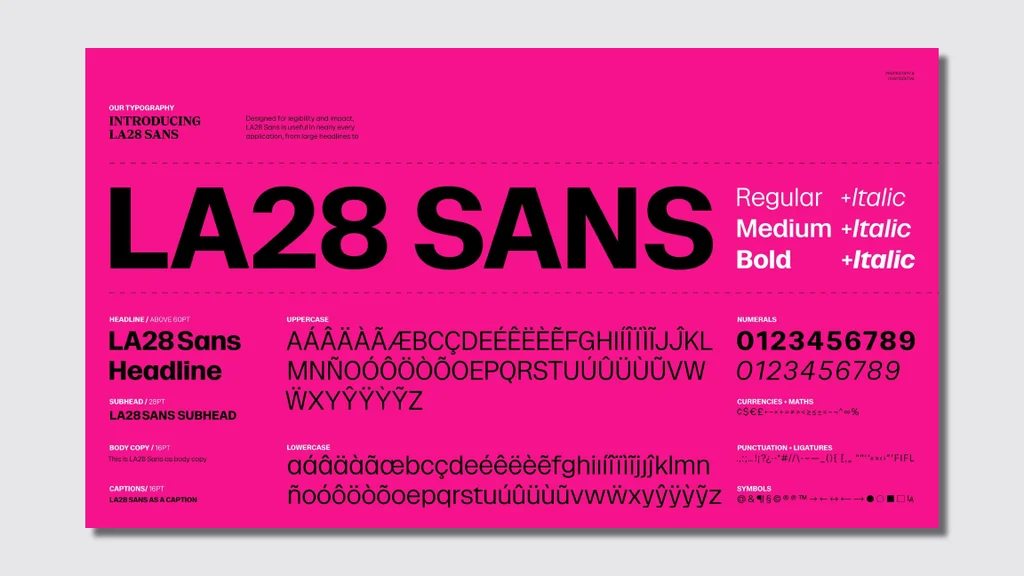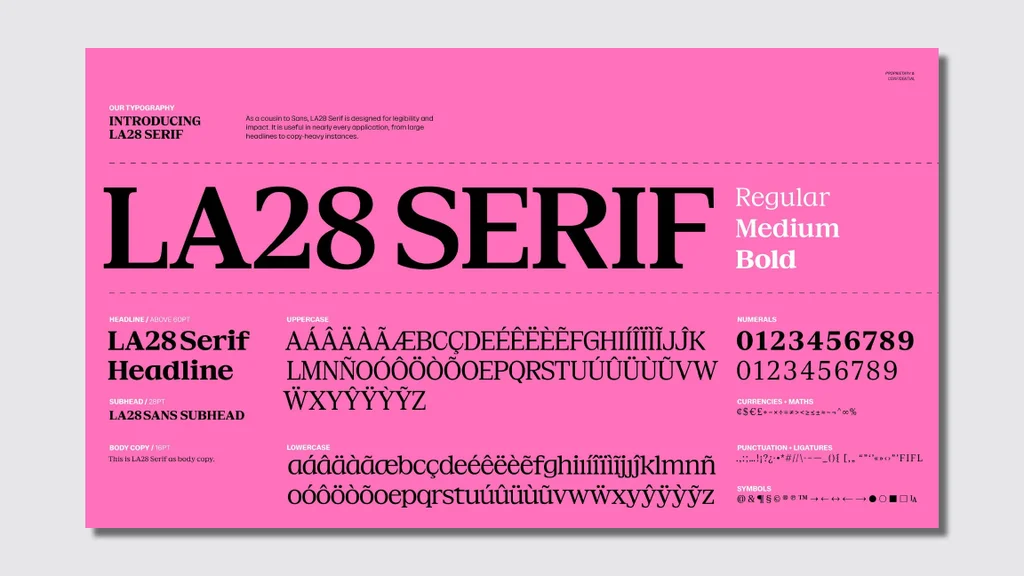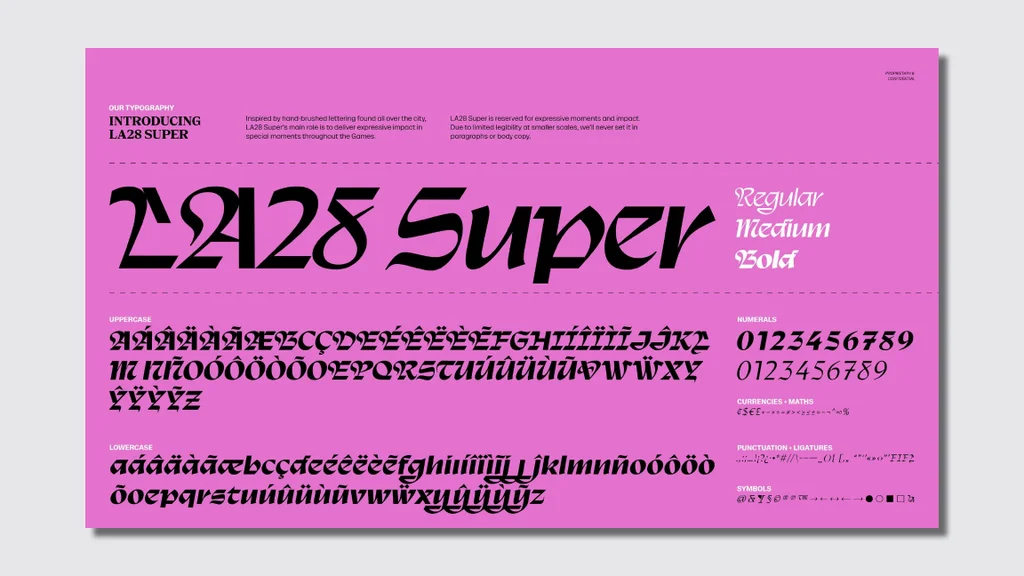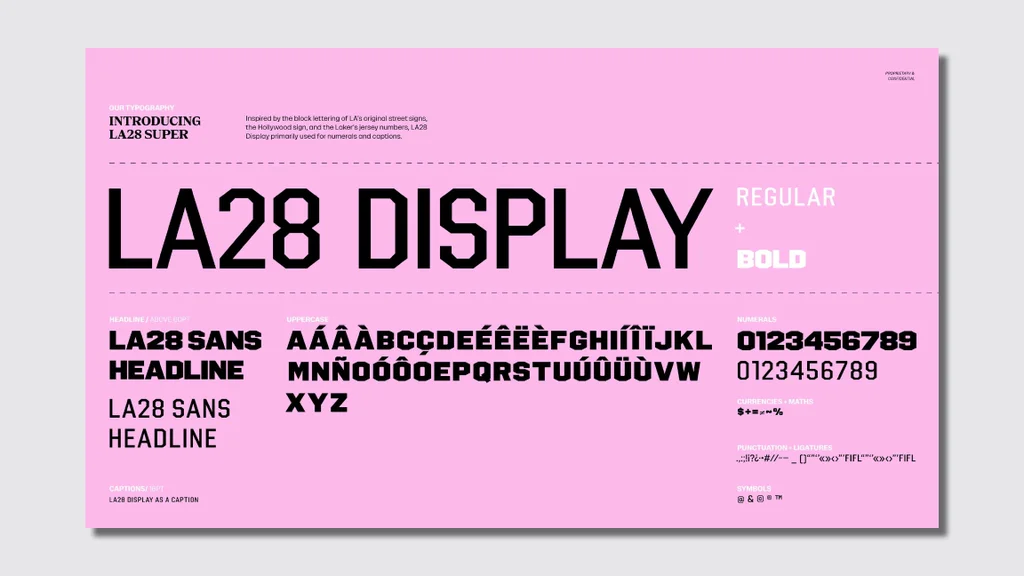
Olimpíadas de LA 2028 já quebram uma tradição do design olímpico
A identidade visual dos Jogos de Los Angeles 2028 abandona a tradição das fontes únicas e aposta em quatro famílias tipográficas inspiradas na diversidade cultural da cidade.
Tipografia LA28 criada para a identidade visual das Olimpíadas de Los Angeles 2028.
A família tipográfica LA28 reúne quatro fontes inspiradas na cultura visual, nos letreiros e na diversidade de Los Angeles.
Quando Los Angeles sediou os Jogos Olímpicos pela última vez, em 1984, os designers trabalhavam com um sistema tipográfico relativamente simples. O logotipo usava a fonte sem serifa Univers 66 em itálico, acompanhada por uma marca "LA84" em estilo estêncil que aparecia na sinalização das arenas e da cidade.
Mais de 40 anos depois, os Jogos Olímpicos de Los Angeles 2028 adotarão uma abordagem bem diferente: um conjunto tipográfico exclusivo composto por quatro fontes.
A família tipográfica criada para a identidade visual dos Jogos de 2028, desenvolvida pelo Koto Studio, chama-se LA28. Inspirada nas fachadas de pequenos comércios, letreiros pintados à mão e na cultura visual das ruas de Los Angeles, ela reúne quatro estilos distintos: Display, Sans, Serif e Super.
Juntas, elas representam uma abordagem muito mais eclética para a tipografia do que aquela que costumamos associar ao design olímpico.
"Queríamos que a tipografia parecesse algo que só pudesse pertencer a Los Angeles."
Segundo Geoff Engelhardt, diretor de design de marca da LA28, o objetivo não era criar uma representação literal da cidade, mas capturar sua atmosfera.
QUATRO FONTES PARA REPRESENTAR UMA CIDADE
Fonte LA28 Display inspirada nas placas históricas das ruas de Los Angeles.
Inspirada na sinalização original das ruas de Los Angeles, a LA28 Display foi criada para números, legendas e sistemas de orientação. Crédito:LA28
A LA28 Display foi inspirada nas letras em bloco presentes nas placas originais das ruas de Los Angeles. Ela foi criada para aplicações como números, legendas e sistemas de orientação.
Fonte LA28 Sans criada para textos e aplicações de alta legibilidade nos Jogos Olímpicos de Los Angeles 2028.
A LA28 Sans prioriza clareza, legibilidade e acessibilidade para aplicações com grande volume de texto. Crédito: LA28
A LA28 Sans foi desenhada para priorizar clareza, legibilidade e acessibilidade, especialmente em textos mais extensos.
Fonte LA28 Super inspirada na cultura urbana e na diversidade visual de Los Angeles.
Expressiva e inspirada na caligrafia, a LA28 Super foi criada para momentos de grande impacto visual.
Já a LA28 Super segue o caminho oposto.
Com aparência expressiva e inspirada na caligrafia, ela foi criada para momentos de maior impacto visual. Um dos exemplos divulgados pela organização mostra um outdoor com a palavra "Bienvenidos", destacando a influência da cultura latina na cidade.
Suas letras combinam ângulos marcados, formas geométricas, curvas suaves e elementos decorativos bastante característicos.
Fonte LA28 Serif desenvolvida para textos longos na identidade visual da LA28.
A LA28 Serif funciona como contraponto à Sans e foi projetada para textos mais extensos.
A quarta integrante da família é a LA28 Serif.
Ela funciona como contraponto à Sans, servindo como fonte de trabalho para grandes volumes de texto. Tanto a Serif quanto a Sans atendem aos requisitos de acessibilidade definidos pela Lei dos Americanos com Deficiências (ADA).
TIPOGRAFIA DAS OLÍMPIADAS LA28
A família tipográfica LA28 reúne quatro estilos distintos: Display, Sans, Serif e Super. Juntas, as quatro fontes criam um sistema visual mais sofisticado do que aqueles vistos em Jogos Olímpicos das últimas décadas.
A escolha reflete a estratégia mais ampla adotada pelos organizadores para construir a identidade visual da LA28, baseada na diversidade cultural da cidade.
"Existe toda uma cultura visual vivendo nas ruas de Los Angeles, nas fachadas das lojas, nos murais pintados à mão e nas letras das placas históricas. Queríamos homenagear isso em vez de importar algo que parecesse estranho à cidade", afirma Ric Edwards, vice-presidente de design de marca e diretor executivo de design da LA28.
A IDENTIDADE VISUAL DOS JOGOS SE INSPIRA NA PRÓPRIA CIDADE
Os Jogos Olímpicos de Los Angeles de 1984 ficaram conhecidos por sua paleta vibrante de cores, presente em elementos como padrões gráficos inspirados em confetes e na cenografia das arenas.
Para 2028, essa herança visual foi reinterpretada por meio de um conceito chamado Superbloom, inspirado na flora do sul da Califórnia e na ave-do-paraíso, flor oficial da cidade.
Cada fonte possui uma personalidade e um propósito específicos.
Os organizadores dizem que enxergam o sistema menos como um guia de estilo e mais como uma composição musical.
Nesse modelo, as fontes funcionam como frequências visuais diferentes, que podem ser combinadas e sobrepostas, mas permanecem sempre em harmonia.